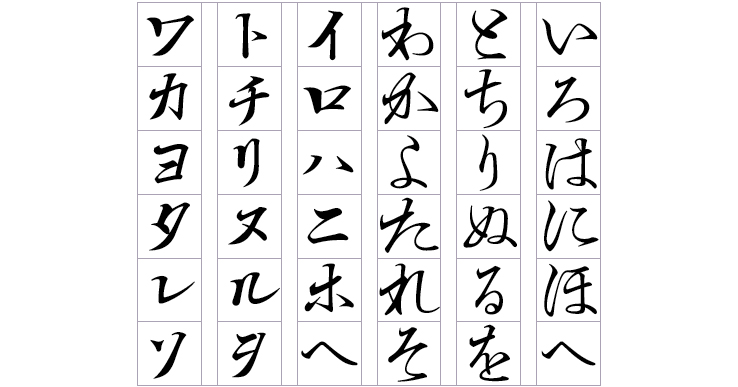
仮名グリフのみ収容
【江川活版三号行書仮名】日本活字史上最も個性的な行書体。唯一無二ともいえるこの行書を揮毫したのは書家の久永其頴(ひさながきえい)。片仮名は筆の腹を使って細太のコントラストを強調、ひらがなは細太の差はないが、その字形は奔放、線質は勁烈で誰でもが書けるものではありません。
江川活版三号行書仮名